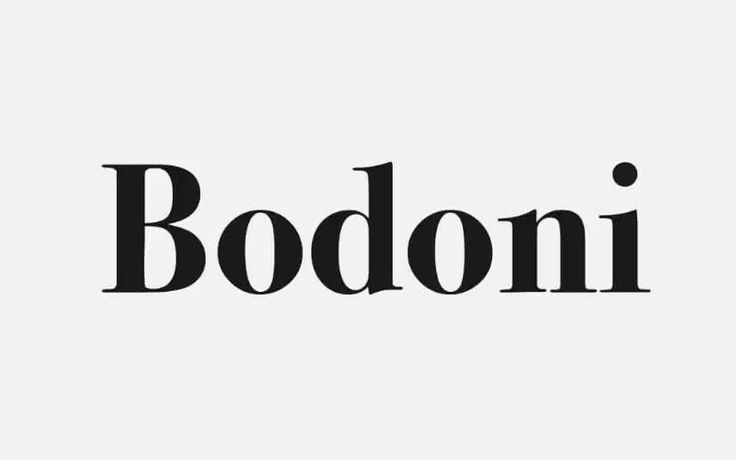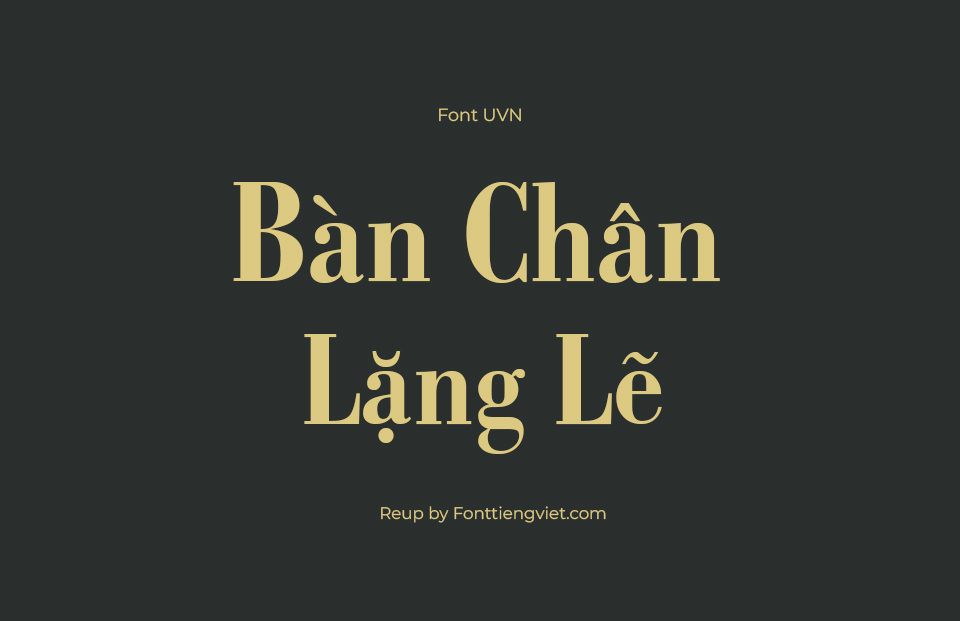
Font Bodoni Việt hóa đẹp
Font Bodoni là một trong những kiểu chữ serif kinh điển, nổi bật với vẻ đẹp thanh lịch, sang trọng và độ tương phản rõ nét giữa các nét dày – mảnh. Được thiết kế bởi Giambattista Bodoni vào cuối thế kỷ 18, font Bodoni là đại diện tiêu biểu cho thời kỳ chuyển tiếp từ kiểu chữ cổ điển sang hiện đại trong thiết kế typographic.
Đặc điểm nổi bật của font Bodoni
Font Bodoni có những đặc trưng rất dễ nhận biết, làm nên sự khác biệt so với nhiều kiểu chữ serif khác:
• Độ tương phản cao giữa nét dày và nét mảnh: Các ký tự trong Bodoni có sự tương phản rõ rệt giữa những nét chính dày và các nét phụ rất mảnh. Sự tương phản này giúp chữ trở nên nổi bật và mạnh mẽ về thị giác.
• Đường cong mềm mại kết hợp với đường thẳng sắc nét: Font Bodoni sử dụng các đường cong uyển chuyển cho phần thân chữ và các chi tiết, kết hợp với các nét thẳng đứng sắc gọn. Điều này mang lại cảm giác tinh tế, hiện đại và có phần thanh lịch.
• Chân chữ (serif) thẳng, mảnh, không cong như serif cổ điển: Khác với các kiểu serif truyền thống có chân chữ bo cong nhẹ, Bodoni có chân chữ thẳng, mảnh, vuông vức. Thiết kế này tạo cảm giác cứng cáp, hiện đại và chỉn chu.
• Mang lại cảm giác trang nhã và mạnh mẽ: Font Bodoni thường được sử dụng trong các ấn phẩm cao cấp vì nó tạo được ấn tượng sang trọng, tinh tế nhưng cũng đầy quyền lực. Rất thích hợp cho các thiết kế cần tạo dấu ấn về phong cách và đẳng cấp.
Ứng dụng của font Bodoni
• Tạp chí thời trang: Những ấn phẩm thời trang danh tiếng như Vogue, Harper’s Bazaar đã sử dụng Bodoni để thể hiện phong cách thanh lịch, quyến rũ và hiện đại.
• Logo các thương hiệu cao cấp: Font Bodoni thường xuất hiện trong thiết kế logo của các thương hiệu thời trang, mỹ phẩm và đồ xa xỉ để tạo nên vẻ sang trọng và đẳng cấp.
• Thiết kế poster, bìa sách, thiệp cưới: Kiểu chữ này được nhiều designer lựa chọn cho các thiết kế in ấn nghệ thuật vì nó dễ gây ấn tượng và mang lại sự chuyên nghiệp.
• Thiết kế nhận diện thương hiệu: Bodoni là lựa chọn lý tưởng cho những thương hiệu muốn hướng tới hình ảnh cổ điển nhưng vẫn hiện đại, chỉn chu và thời thượng.
Font Bodoni không chỉ là một kiểu chữ serif đơn thuần, mà còn là biểu tượng của sự thanh lịch, đẳng cấp và chuyên nghiệp trong thiết kế. Với độ tương phản cao, nét chữ tinh tế và cấu trúc mạnh mẽ, Bodoni đặc biệt phù hợp cho các ấn phẩm thời trang, thương hiệu cao cấp, hay những thiết kế cần tạo ấn tượng thị giác mạnh. Dù mang hơi hướng cổ điển, Bodoni vẫn giữ được sự hiện đại và không hề lỗi thời, luôn là lựa chọn hàng đầu cho những nhà thiết kế theo đuổi phong cách sang trọng và tinh tế.